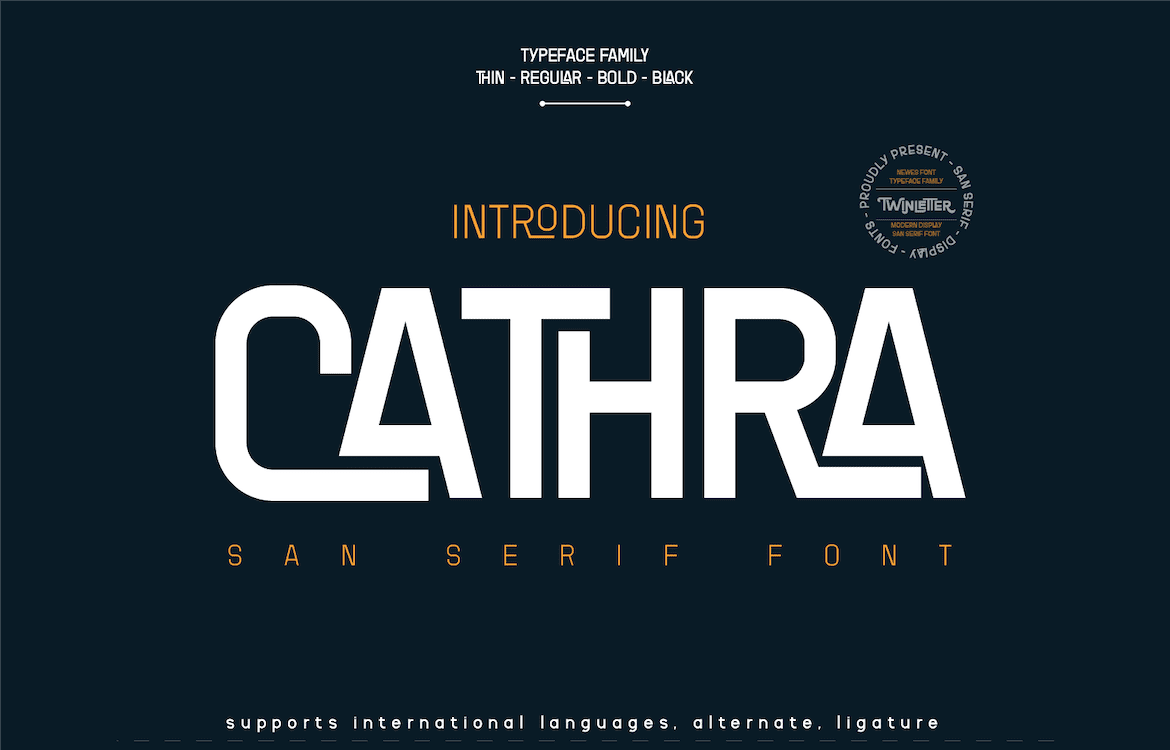
Представляем вам наш новый шрифт Cathra.
Шрифт, который обогащен переменным семейством шрифтов для нужд слов, а также текста, также оснащен красивыми лигатурами и чередованием некоторых букв.
Мы разработали этот шрифт семейства San Serif, обратив внимание на сочетание каждой буквы, чтобы создать красивое впечатление и внешний вид, что облегчает удовлетворение ваших потребностей, как формальных, так и неформальных.
Этот шрифт идеально подходит для самых разных дизайнерских проектов, спортивных мероприятий, брендинга, баннеров, плакатов, названий фильмов, продуктов питания и напитков, технологий, цитат, одежды, логотипов и многого другого.
Конечно, ваши различные дизайнерские проекты будут идеальными и удивительными, если вы используете этот шрифт, потому что этот шрифт поставляется с семейством шрифтов, как для заголовков, так и для подзаголовков и текста предложений, начните использовать наши шрифты для ваших удивительных проектов.